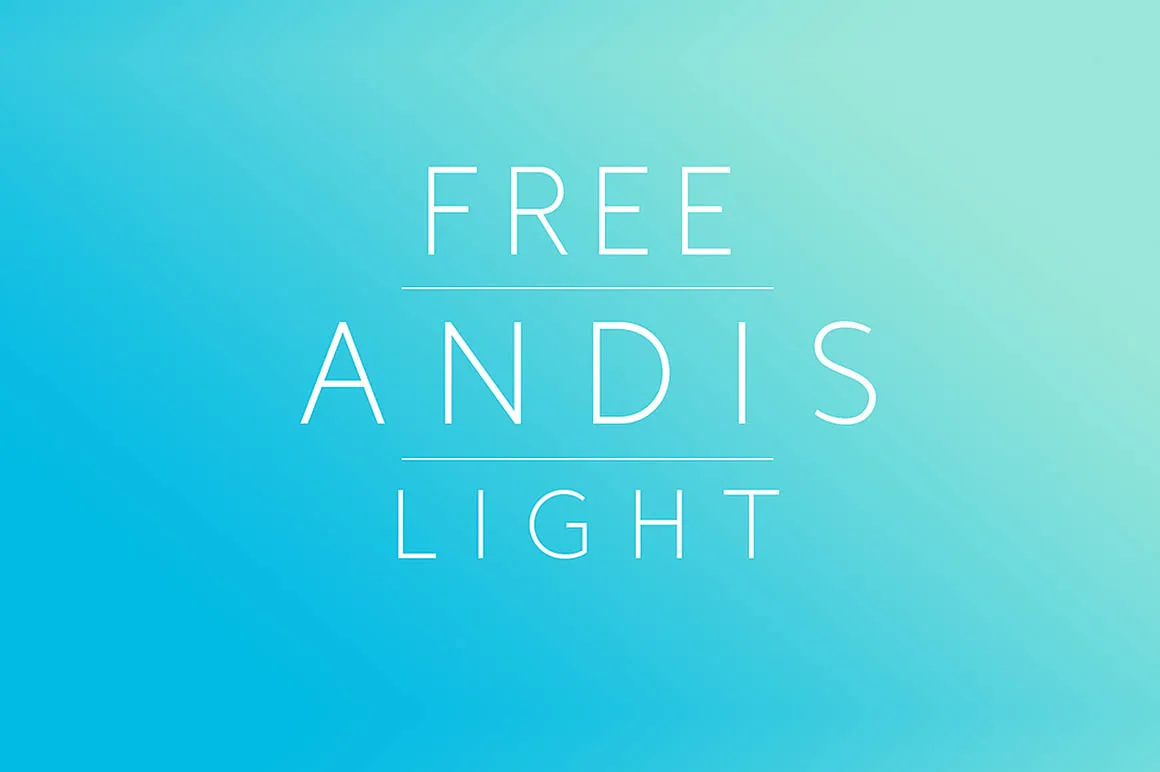
Andis Light Font – Fonte Grátis
Andis Light Font
A fonte Andis Light é uma escolha perfeita para quem procura um tipo sans-serif que seja tanto alegre quanto funcional. Seu designer, Hamilton, criou este tipo de fonte com rachaduras fortes e uma x-height generosa, o que torna Andis Light ideal não só para aplicações visuais mais elaboradas, mas também para títulos ou parágrafos em texto tamanho grande. Com sua tipografia leve, a Andis mantém um toque firme sem perder a fluididade necessária para grandes fontes legíveis e de fácil leitura. Adicionar esta fonte ao seu design pode transformar o texto numa obra-prima visual, tornando suas criações ainda mais impactantes e divertidas.